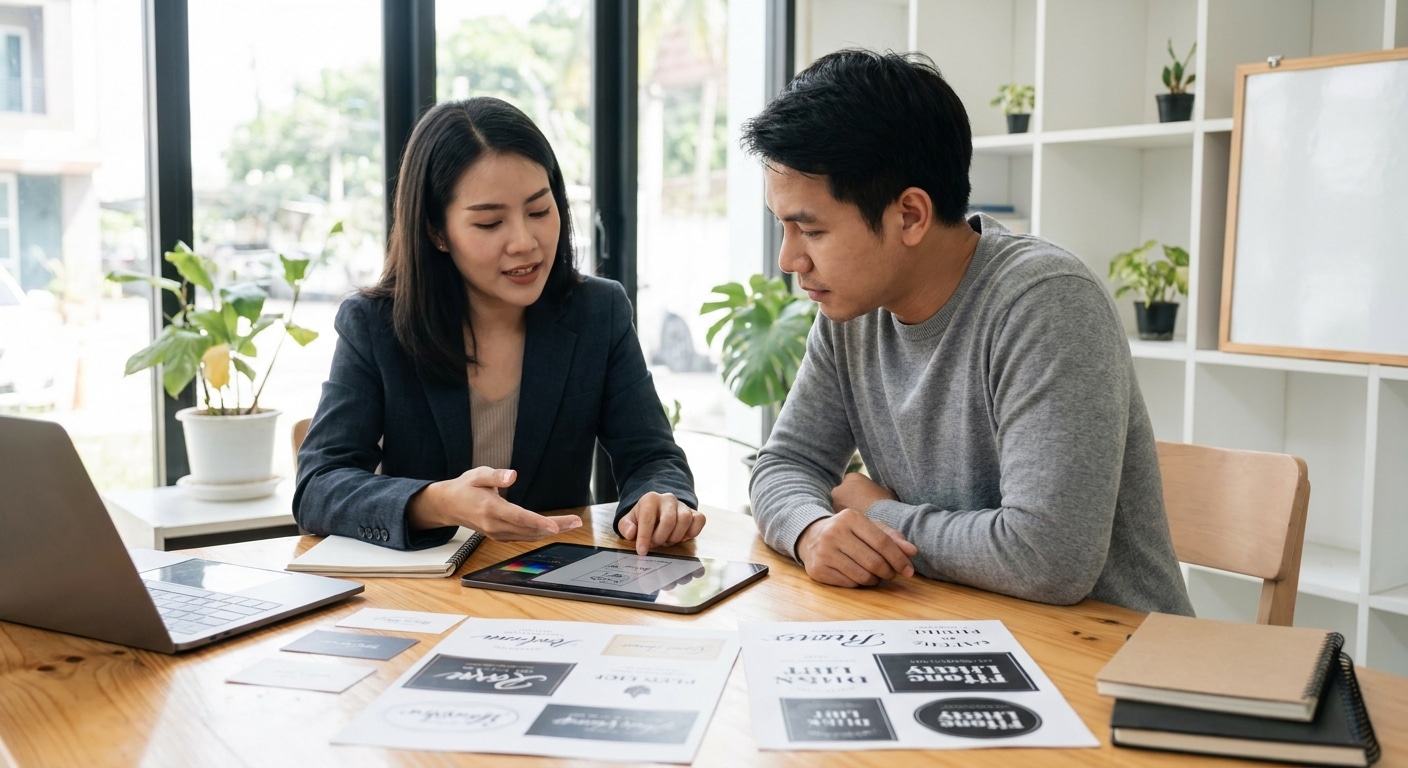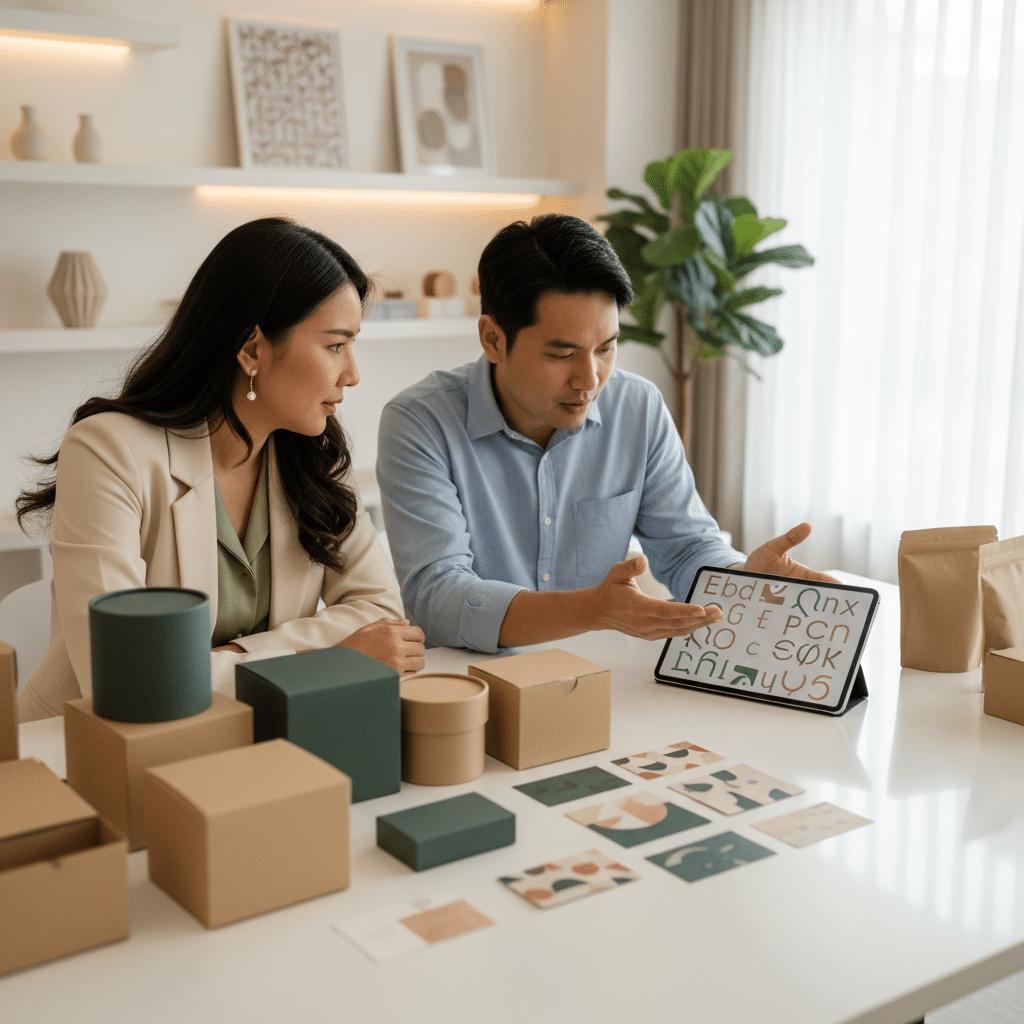
เทคนิคเลือกฟอนต์นามบัตรและฉลากสินค้า ดึงดูดลูกค้า SME
การเลือกแบบอักษรหรือฟอนต์สำหรับสื่อสิ่งพิมพ์ไม่ใช่เป็นเพียงเรื่องของความสวยงาม แต่เป็นองค์ประกอบสำคัญในการสร้างแบรนด์ที่ส่งผลโดยตรงต่อการรับรู้ของลูกค้า โดยเฉพาะสำหรับธุรกิจ SME ที่การสร้างความประทับใจแรกเป็นสิ่งจำเป็นอย่างยิ่ง บทความนี้จะนำเสนอเทคนิคเลือกฟอนต์นามบัตรและฉลากสินค้า ดึงดูดลูกค้า SME อย่างมืออาชีพ เพื่อสร้างภาพลักษณ์ที่น่าจดจำและเพิ่มมูลค่าให้กับผลิตภัณฑ์
หัวใจสำคัญของการเลือกฟอนต์สำหรับธุรกิจ
- สะท้อนบุคลิกของแบรนด์: ฟอนต์ที่เลือกใช้ควรสอดคล้องกับภาพลักษณ์ของแบรนด์ ไม่ว่าจะเป็นความหรูหรา ความเป็นมิตร หรือความทันสมัย
- สื่อสารอย่างชัดเจน: ความอ่านง่ายเป็นปัจจัยสำคัญที่สุด ฟอนต์ที่ซับซ้อนเกินไปอาจทำให้ข้อมูลสำคัญถูกมองข้ามไป
- สร้างความแตกต่าง: การเลือกฟอนต์ที่เป็นเอกลักษณ์ช่วยให้ผลิตภัณฑ์และนามบัตรโดดเด่นกว่าคู่แข่งในตลาด
- สร้างการจดจำ: การใช้ฟอนต์อย่างสม่ำเสมอในทุกสื่อสิ่งพิมพ์จะช่วยสร้างการจดจำแบรนด์ในระยะยาว
สำหรับผู้ประกอบการ SME การทำความเข้าใจเกี่ยวกับเทคนิคเลือกฟอนต์นามบัตรและฉลากสินค้า ดึงดูดลูกค้า SME ถือเป็นกลยุทธ์การตลาดต้นทุนต่ำที่มีประสิทธิภาพสูง ฟอนต์ไม่ได้เป็นเพียงตัวอักษร แต่เป็นเสียงของแบรนด์ (Brand Voice) ที่สื่อสารกับลูกค้าโดยไม่ต้องเอ่ยคำพูด การเลือกฟอนต์ที่เหมาะสมสามารถสร้างความน่าเชื่อถือ ทำให้สินค้าดูมีราคา และกระตุ้นการตัดสินใจซื้อได้ ในทางกลับกัน การเลือกฟอนต์ที่ไม่เหมาะสมอาจทำให้แบรนด์ดูไม่เป็นมืออาชีพและลดทอนคุณค่าของสินค้าลง
บทความนี้จะเจาะลึกถึงประเภทของฟอนต์ต่างๆ หลักการเลือกใช้ให้เข้ากับธุรกิจ และตัวอย่างการประยุกต์ใช้ในการออกแบบนามบัตรและฉลากสินค้า เพื่อให้ผู้ประกอบการสามารถนำความรู้ไปปรับใช้ สร้างสรรค์สื่อสิ่งพิมพ์ที่ทรงพลังและส่งเสริมยอดขายได้อย่างยั่งยืน
ทำความเข้าใจประเภทฟอนต์: เลือกใช้ให้ตรงจุดประสงค์
ก่อนจะเริ่มออกแบบ สิ่งสำคัญคือการทำความรู้จักกับประเภทฟอนต์หลักๆ ซึ่งแต่ละประเภทมีบุคลิกและสื่อสารอารมณ์ที่แตกต่างกัน การเลือกใช้ให้ถูกกับบริบทของแบรนด์และผลิตภัณฑ์จึงเป็นก้าวแรกสู่ความสำเร็จ
ฟอนต์มีเชิง (Serif): ความคลาสสิกและน่าเชื่อถือ
ฟอนต์ประเภท Serif มีลักษณะเด่นคือมี “เชิง” หรือเส้นเล็กๆ ที่ปลายตัวอักษร ฟอนต์กลุ่มนี้ให้ความรู้สึกที่เป็นทางการ คลาสสิก สง่างาม และน่าเชื่อถือ มักพบเห็นได้ในสื่อสิ่งพิมพ์ที่เป็นเนื้อหายาวๆ เช่น หนังสือ นิตยสาร หรืองานพิมพ์ที่ต้องการสร้างความรู้สึกมั่นคงและเป็นมืออาชีพ
การประยุกต์ใช้: เหมาะสำหรับนามบัตรของธุรกิจที่ต้องการสร้างความน่าเชื่อถือสูง เช่น บริษัทกฎหมาย สถาบันการเงิน หรือที่ปรึกษาทางธุรกิจ นอกจากนี้ยังเหมาะกับฉลากสินค้าของแบรนด์ที่มีประวัติยาวนาน หรือผลิตภัณฑ์ที่ต้องการสื่อถึงความเป็นต้นตำรับและคุณภาพระดับพรีเมียม
ตัวอย่างฟอนต์: Times New Roman, Garamond, Georgia
ฟอนต์ไม่มีเชิง (Sans-serif): ความทันสมัยและเรียบง่าย
“Sans” เป็นภาษาฝรั่งเศสแปลว่า “ไม่มี” ดังนั้น Sans-serif จึงหมายถึงฟอนต์ที่ไม่มีเชิงที่ปลายตัวอักษร ทำให้ดูสะอาดตา เรียบง่าย และทันสมัย ฟอนต์ประเภทนี้อ่านง่ายบนหน้าจอดิจิทัลและในพื้นที่ขนาดเล็ก จึงได้รับความนิยมอย่างสูงในปัจจุบัน
การประยุกต์ใช้: เป็นตัวเลือกที่ยอดเยี่ยมสำหรับธุรกิจ SME สไตล์โมเดิร์น บริษัทเทคโนโลยี หรือสตาร์ทอัพ ในการออกแบบฉลากสินค้า ฟอนต์ Sans-serif ช่วยให้ข้อมูลส่วนผสมหรือรายละเอียดสินค้าอ่านง่ายและชัดเจน แม้จะมีขนาดเล็กก็ตาม สำหรับนามบัตร ฟอนต์กลุ่มนี้สื่อถึงความตรงไปตรงมาและเข้าถึงง่าย ฟอนต์อย่าง Myriad Pro เป็นตัวเลือกที่หลากหลาย สามารถใช้ได้ทั้งบนนามบัตร โฆษณา และสื่อดิจิทัล ให้ความรู้สึกหรูหราแต่ยังคงความทันสมัย
ตัวอย่างฟอนต์: Arial, Helvetica, Futura, Myriad Pro
ฟอนต์ลายมือ (Script): ความหรูหราและเป็นกันเอง
ฟอนต์ประเภท Script เลียนแบบลายมือเขียน ให้ความรู้สึกที่เป็นส่วนตัว เป็นกันเอง และหรูหรา มีความลื่นไหลและมีศิลปะสูง อย่างไรก็ตาม ฟอนต์ประเภทนี้มักจะอ่านยากหากใช้กับข้อความยาวๆ หรือมีขนาดเล็กเกินไป
การประยุกต์ใช้: ควรใช้ฟอนต์ Script อย่างจำกัด เพื่อเน้นข้อความสำคัญ เช่น ชื่อแบรนด์ โลโก้ หรือชื่อรุ่นสินค้าบนฉลากที่ต้องการความพรีเมียม เช่น ผลิตภัณฑ์เครื่องสำอาง ไวน์ หรือสินค้าทำมือ ไม่เหมาะกับการใช้ระบุข้อมูลติดต่อบนนามบัตรหรือรายละเอียดส่วนผสมบนฉลากสินค้า เพราะจะทำให้อ่านได้ยาก
ตัวอย่างฟอนต์: Pacifico, Lobster, Great Vibes
ฟอนต์ตกแต่ง (Display): โดดเด่นและดึงดูดสายตา
ฟอนต์ตกแต่งหรือ Display ถูกออกแบบมาเพื่อสร้างความโดดเด่นและดึงดูดความสนใจในทันที มักมีลักษณะเฉพาะตัวสูงและมีเอกลักษณ์ไม่เหมือนใคร เหมาะสำหรับใช้ในขนาดใหญ่เพื่อเป็นหัวข้อหลัก
การประยุกต์ใช้: เหมาะอย่างยิ่งสำหรับใช้เป็นชื่อสินค้าตัวใหญ่บนฉลาก เพื่อให้สะดุดตาบนชั้นวาง หรือใช้เป็นหัวข้อบนโบรชัวร์และสื่อส่งเสริมการขาย แต่ควรหลีกเลี่ยงการใช้ฟอนต์ประเภทนี้กับเนื้อหาหลักหรือข้อความยาวๆ เพราะจะทำให้อ่านยากและดูลายตาเกินไป
ตัวอย่างฟอนต์: Impact, Bebas Neue, Alfa Slab One
| ประเภทฟอนต์ | บุคลิกและลักษณะเด่น | เหมาะสำหรับ |
| Serif (มีเชิง) | เป็นทางการ, คลาสสิก, น่าเชื่อถือ, สง่างาม | นามบัตรธุรกิจดั้งเดิม, ฉลากสินค้าพรีเมียม, เนื้อหายาว |
| Sans-serif (ไม่มีเชิง) | ทันสมัย, เรียบง่าย, สะอาดตา, อ่านง่าย | นามบัตรบริษัทเทคโนโลยี, ฉลากสินค้าทั่วไป, สื่อดิจิทัล |
| Script (ลายมือ) | หรูหรา, เป็นกันเอง, มีศิลปะ, ส่วนตัว | โลโก้, ชื่อสินค้าบนฉลากสินค้าหรูหรา, การ์ดเชิญ |
| Display (ตกแต่ง) | โดดเด่น, สร้างสรรค์, ดึงดูดสายตา, มีเอกลักษณ์ | หัวข้อใหญ่บนฉลากสินค้า, ชื่อแคมเปญส่งเสริมการขาย |
เทคนิคเลือกฟอนต์นามบัตรและฉลากสินค้า ดึงดูดลูกค้า SME
หลังจากทำความเข้าใจประเภทของฟอนต์แล้ว ขั้นตอนต่อไปคือการนำความรู้มาประยุกต์ใช้กับหลักการออกแบบ เพื่อสร้างสรรค์สื่อสิ่งพิมพ์ที่สื่อสารได้อย่างมีประสิทธิภาพและสร้างเอกลักษณ์ให้กับแบรนด์